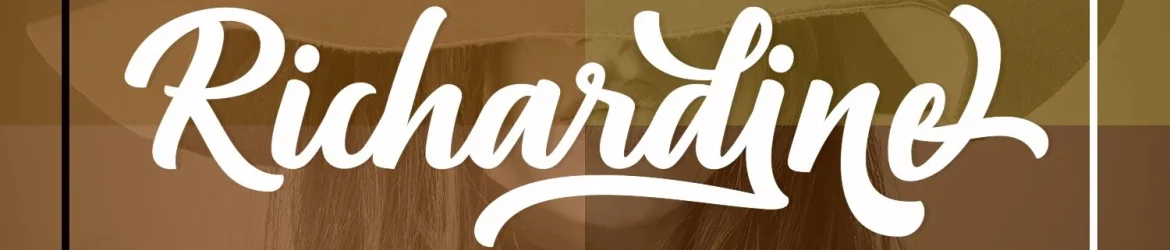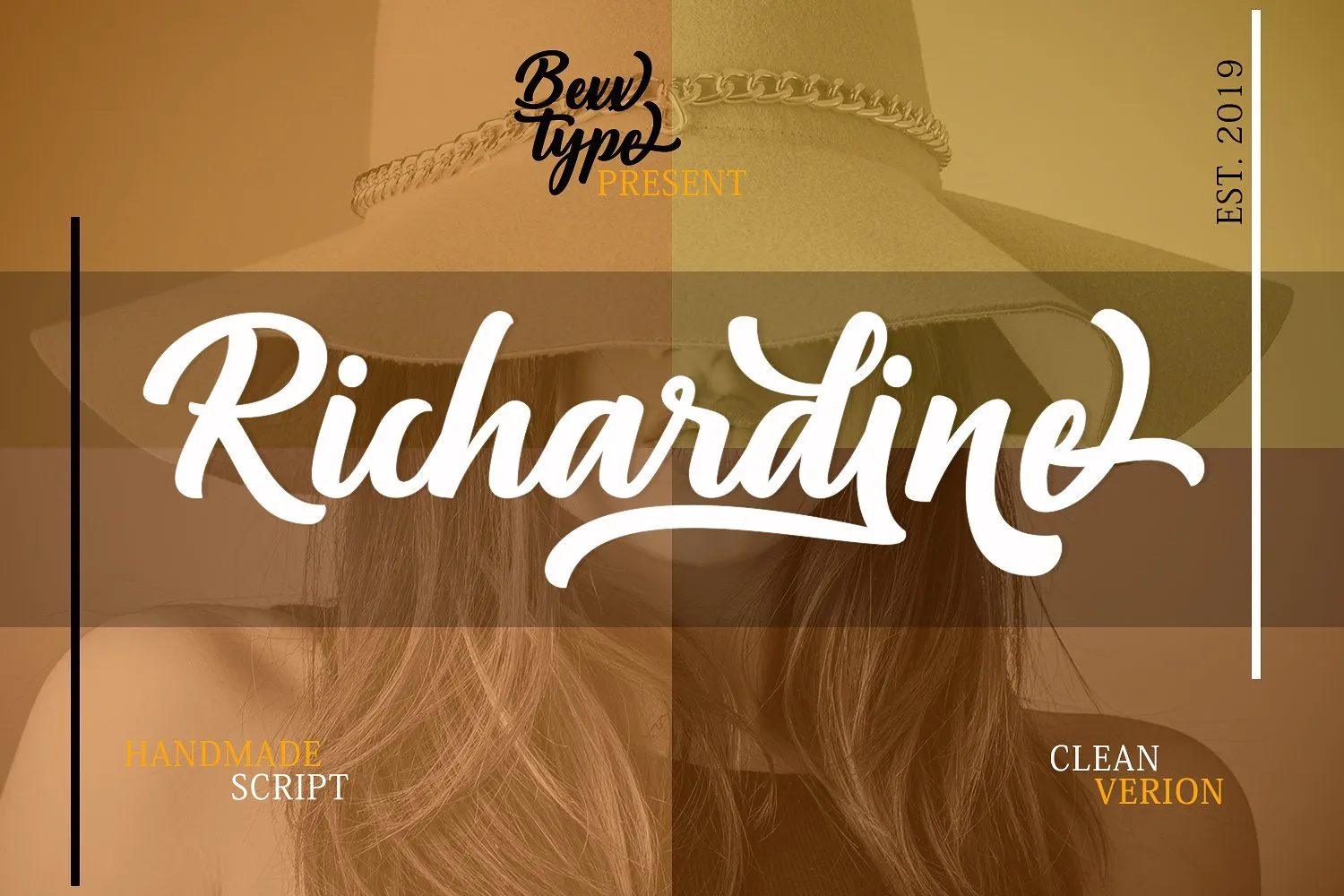
Richardine Script Font – Fonte Grátis
Richardine Script Font
A Richardine Script Font é uma elegante escolha para designers que buscam uma mistura atemporal de modernidade e nostalgia. Ela é perfeita para criações de marca, sua forte presença no preview ilustra seu potencial. Richardine se destaca como um fonte de sinalização retro, bold e limpa, com inúmeras variações em cada caractere. Inclui alternativas estilísticas do OpenType. É fácil e rápido criar layouts tipográficos variados com esta fonte. Aproveite o poder do OpenType, simplesmente abra a paleta de gírias para acessar todos os símbolos. Esta font é perfeita para t-shirts, sinalização, logotipos, headlines, marcações, embalagens e muito mais. Engane-se em pensá-la vintage sem perder seu vigor moderno. Seja você um designer de gráficos ou uma empresa que busca manter sua identidade inovadora e atemporal ao mesmo tempo, Richardine Script é a fonte ideal para você.